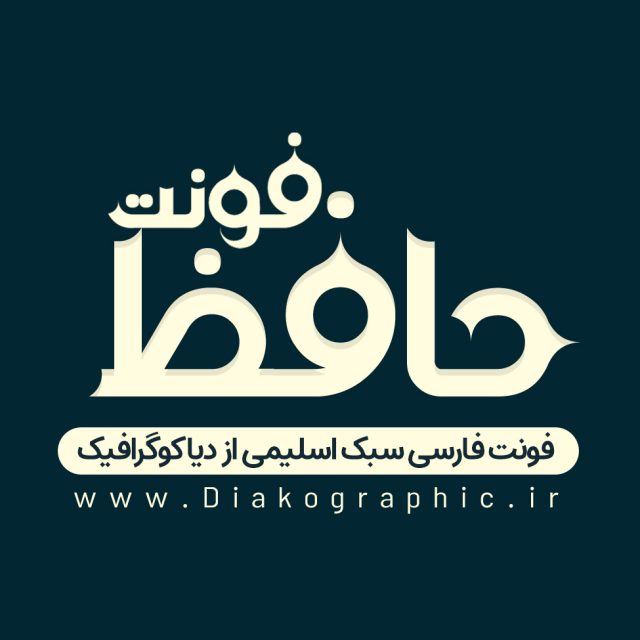
دانلود فونت فارسی حافظ
فونت فارسی حافظ در نسخه جدید منتشر شد! اگر به دنبال یک فونت کامل برای تایپوگرافی با حالت های خاص هستید،فونت حافظ را به هیچ وجه از دست ندهید.طراحی این فونت جذابیت و حرفه ای بودن را به تایپوگرافی های شما می بخشد و می توانید لذت یک تایپ حرفه ای را با این فونت تجربه کنید.از این تایپ فیس میتوانید در تمامی برنامه ها بدون محدودیت استفاده کنید.
برخی ویژگی های فونت فارسی حافظ
- مناسب برای طراحی لوگو تایپ های حرفه ای
- شامل سه نسخه متفاوت و حرفه ای
- دارای دو وزن ریگولار و بولد